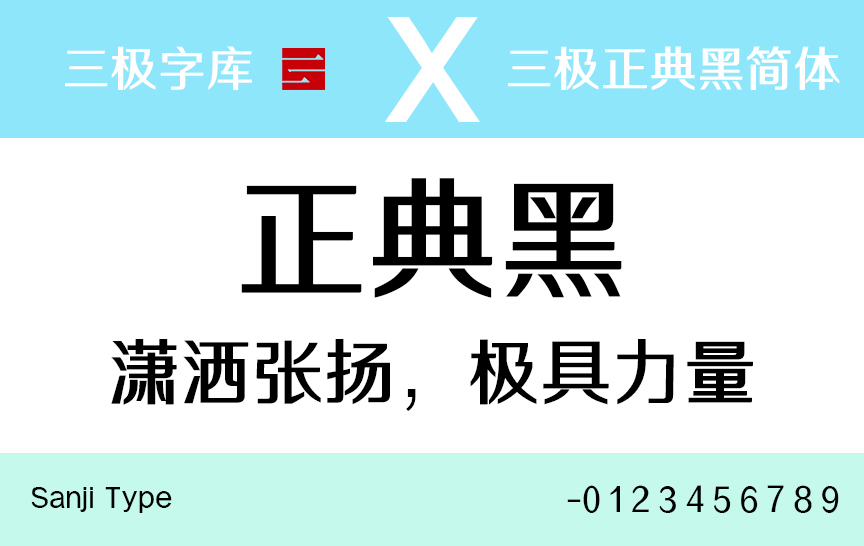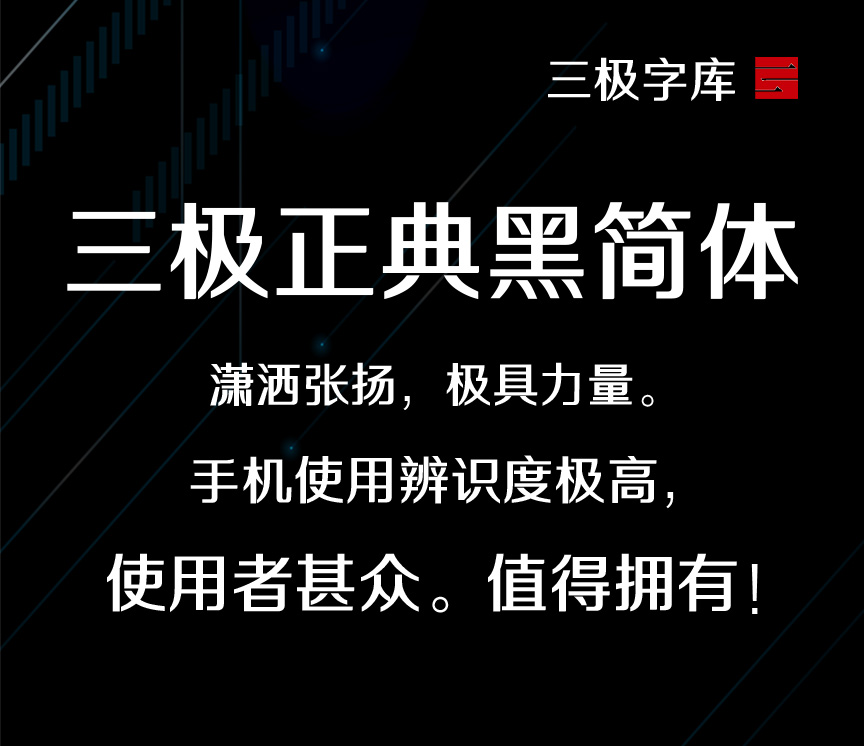
三极正极黑简体作品整体风格鲜明方正,字体结构干练简洁稳重大气,笔画平直、竖粗横细,撇捺镜像对称稳健。起笔收笔平直,折、钩转折明显,圆润饱满。它的灵感来源于黑体,又富有变化,给人一种庄重的感觉,具有婉转柔和的气质。视觉效果简洁易识别,实用性强。本作品适用于传统印刷媒介的标题与正文排版、各类屏幕显示及影视字幕等。